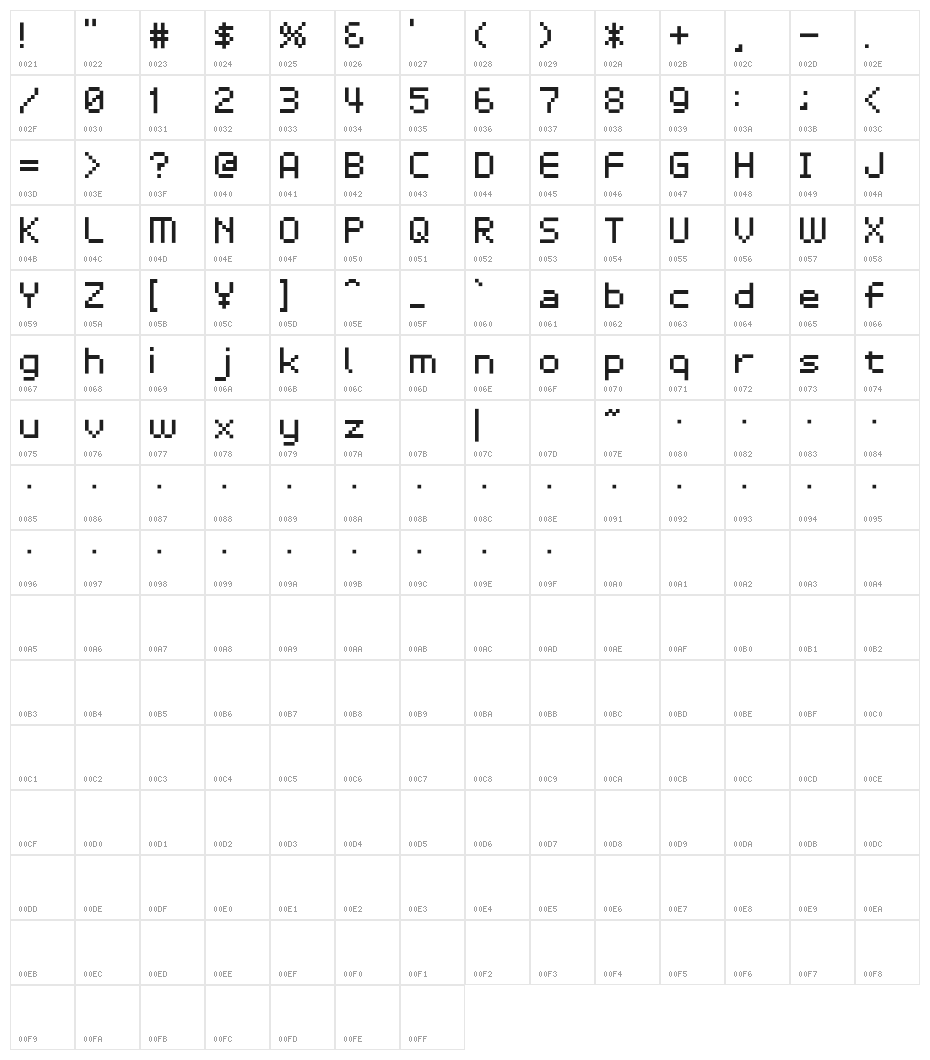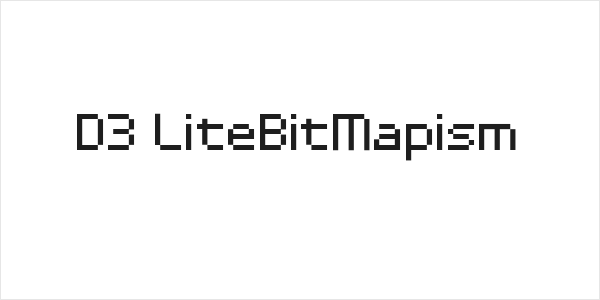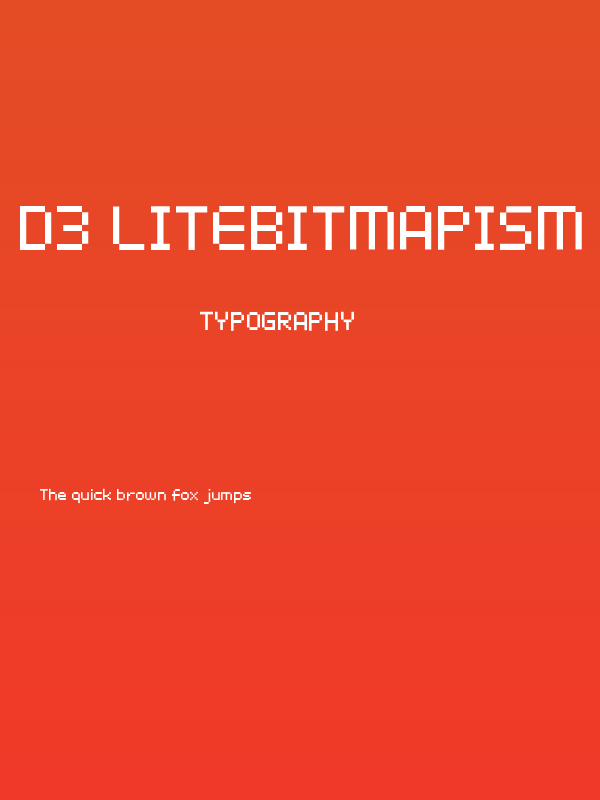
D3 LiteBitMapism Font
| Gesamtstil | Vintage |
| Anwendungsfall | Logos, Posters, Digital Art |
| Vorgeschlagene Projekte | Ideal for retro video game graphics, digital art projects, and designs that require a vintage digital feel. |